デザインやお絵描きでファンタジーや童話的などの雰囲気を出したい時、フォントもかわいいものを使用することがおすすめです。本記事ではかわいくて使えるフォント10選をまとめてみました。興味がある方はぜひ読んでみてください。
ゆずポップは丸みのある手書き風のフォントです。太さも4種類用意されているので、雰囲気に合わせて選ぶことが出来ます。かわいらしい雰囲気で、かつ可視性も高いです。
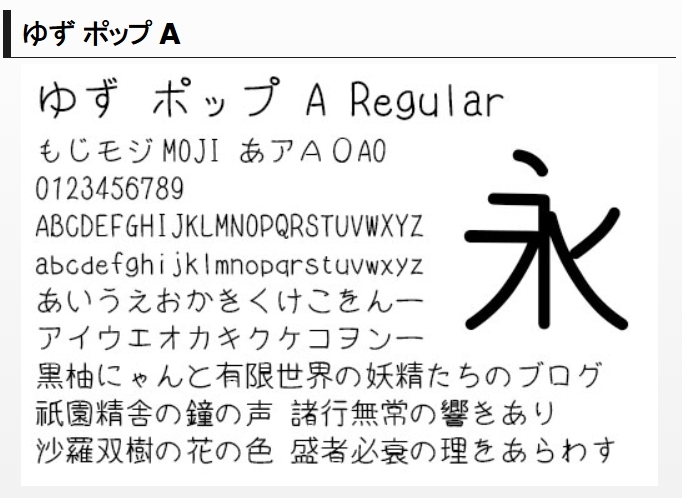
ハンまるゴシックは半角のように見える、細長のゴシック体フォントです。細めの見た目なのに丸っこく、かわいらしさとスタイリッシュさを兼ね備えているので、様々なシーンに使えるフォントとなっています。
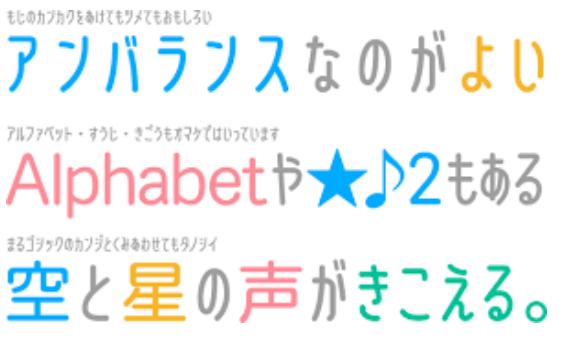
ちはや角は名前の通りカクカクとしたデザインのフォントです。カクカクはしていますが、独特のかわいらしさがあり、他では見ない珍しいデザインとなっています。
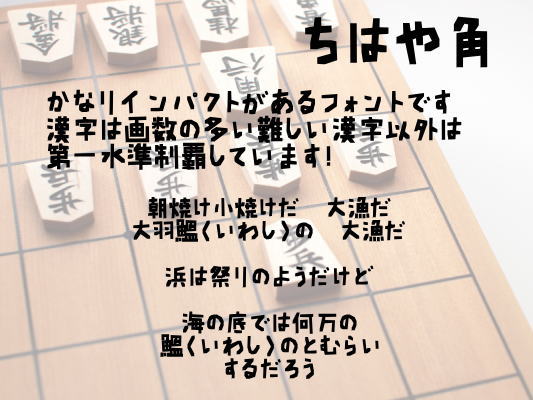
ribbonはリボンでできたような見た目のフォントです。可愛らしく、かつレトロな雰囲気もあり、特に女性の目を引くデザインとなっています。
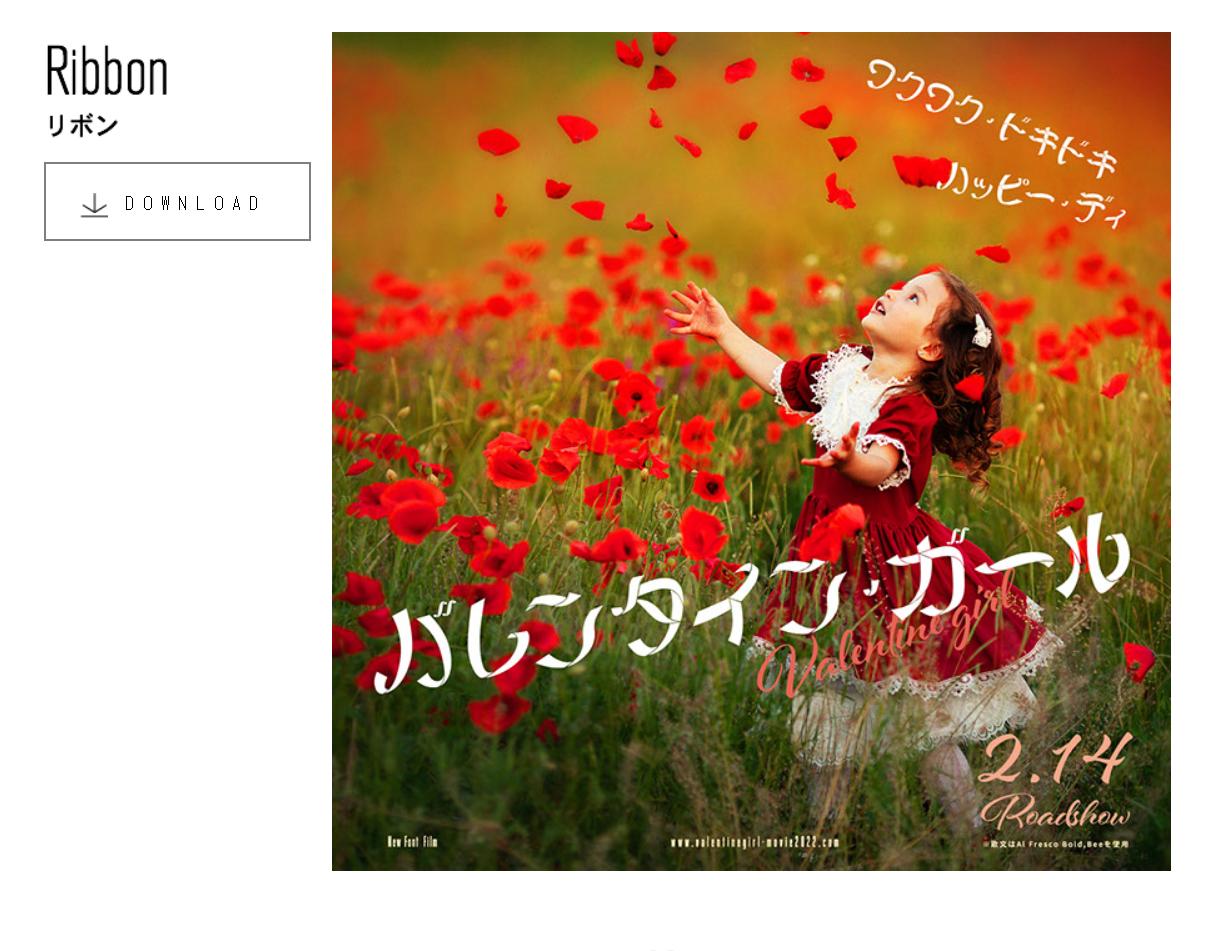
モギハ・ペン字は万年筆で書いたような雰囲気を楽しめるフォントです。かわいらしさの中に、凛とした美しさが感じられます。
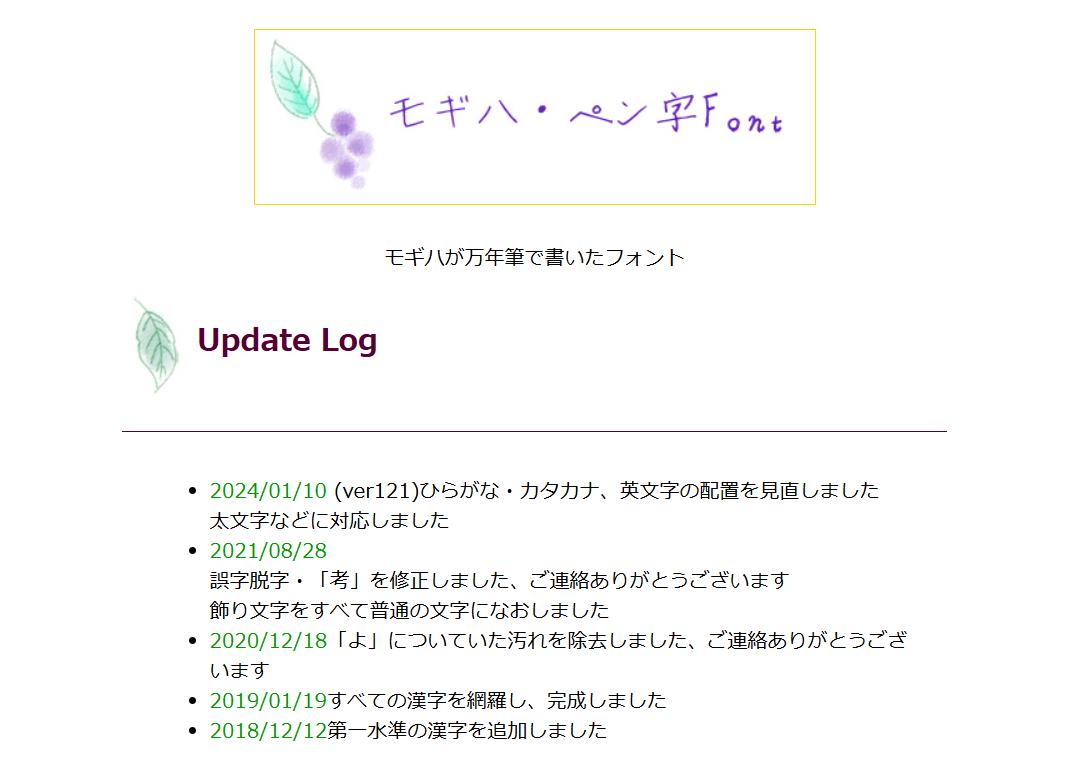
キリンフォントは名前の通り、キリンのように細長いフォントです。細長くカクカクとしていて、かつ太さもあるフォントなので、デザイン性が高く読みやすさもあります。
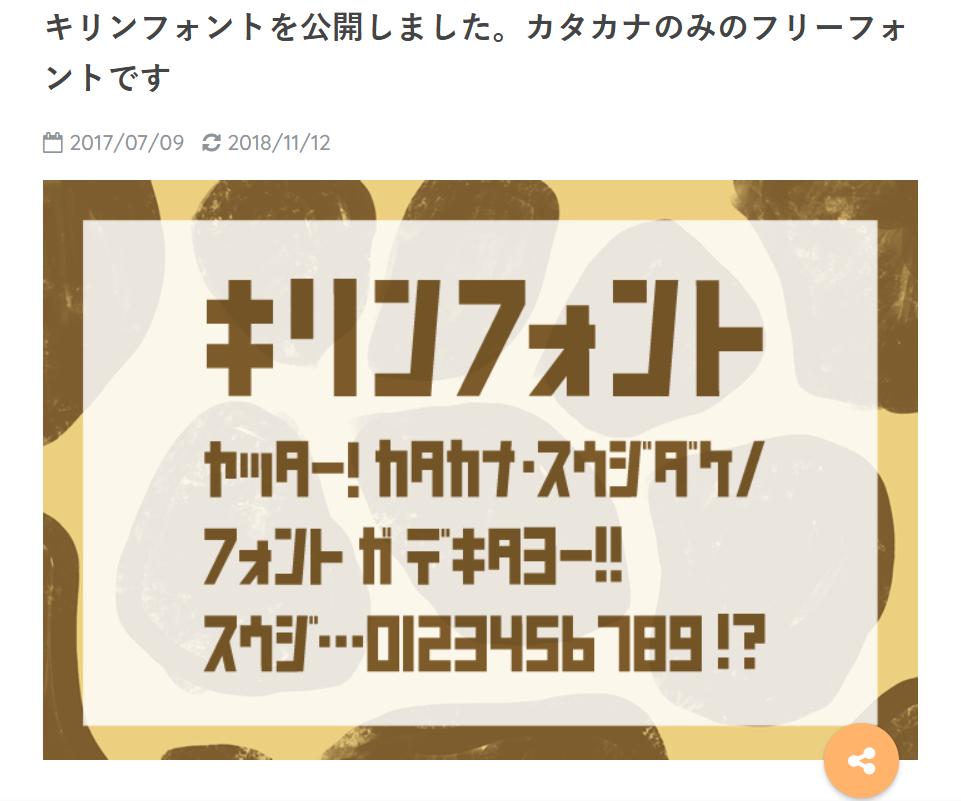
MPRばるーんは全ての文字のグリフに風船のシルエットが入っているフォントです。バルーンのシルエットが表示されるので、タイトルや見出しに使うと非常に目を引きます。
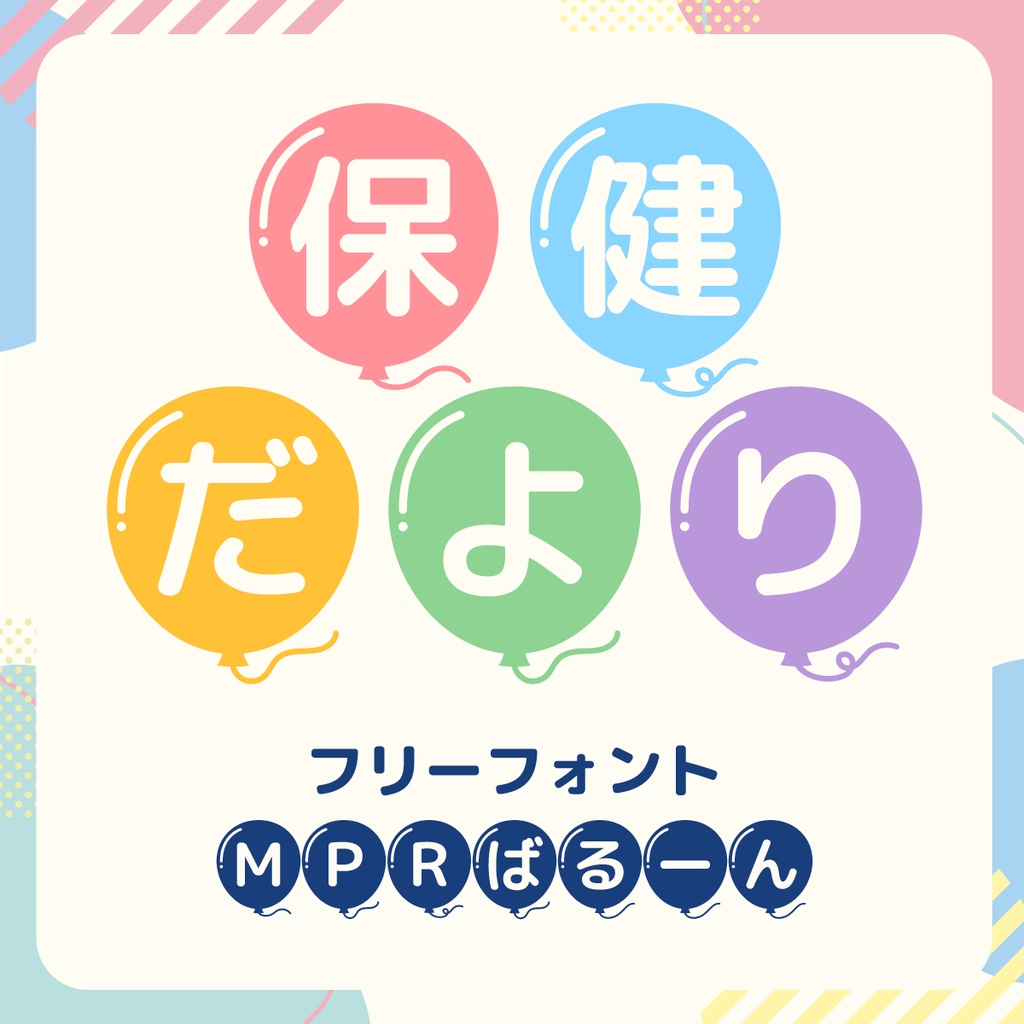
塩化速記は手書きで速記したような見た目のフォントです。柔らかな雰囲気と、リアルな手書き感が印象的なデザインとなっています。
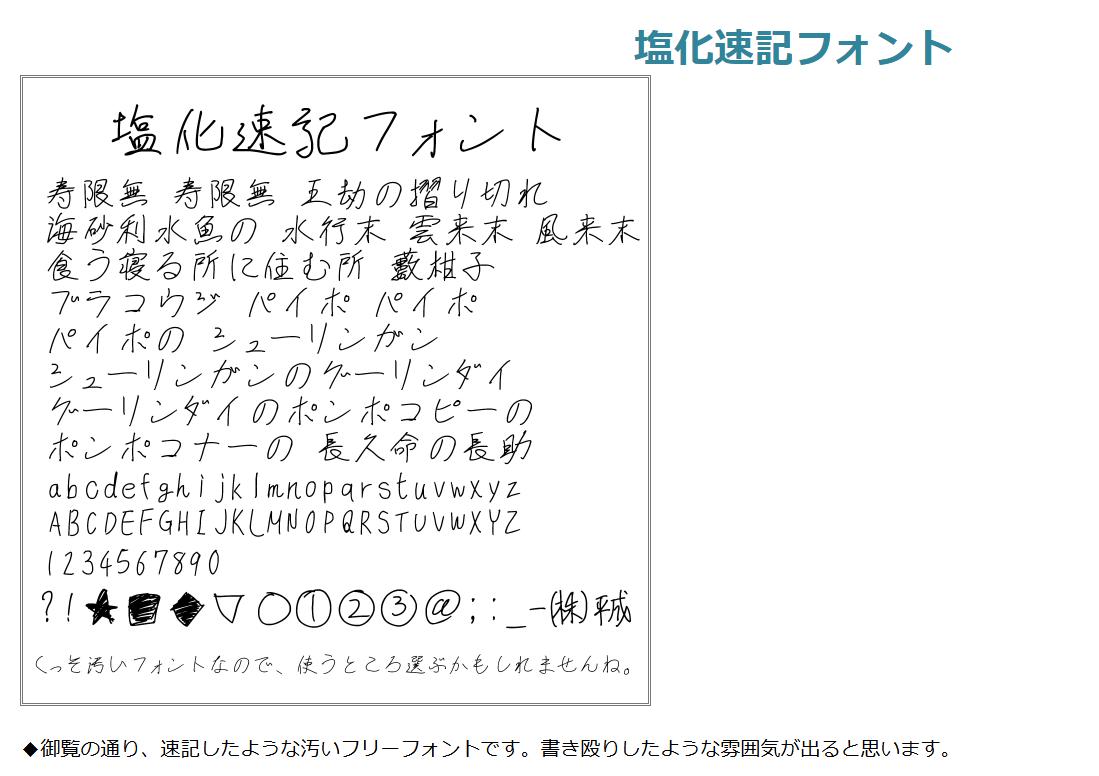
ちひろもじ
ちひろもじは、昔ながらの丸文字やギャル文字のような雰囲気のあるかわいらしいフォントです。手書きの温かみがありながら可視性も高いため、使い勝手が良いです。
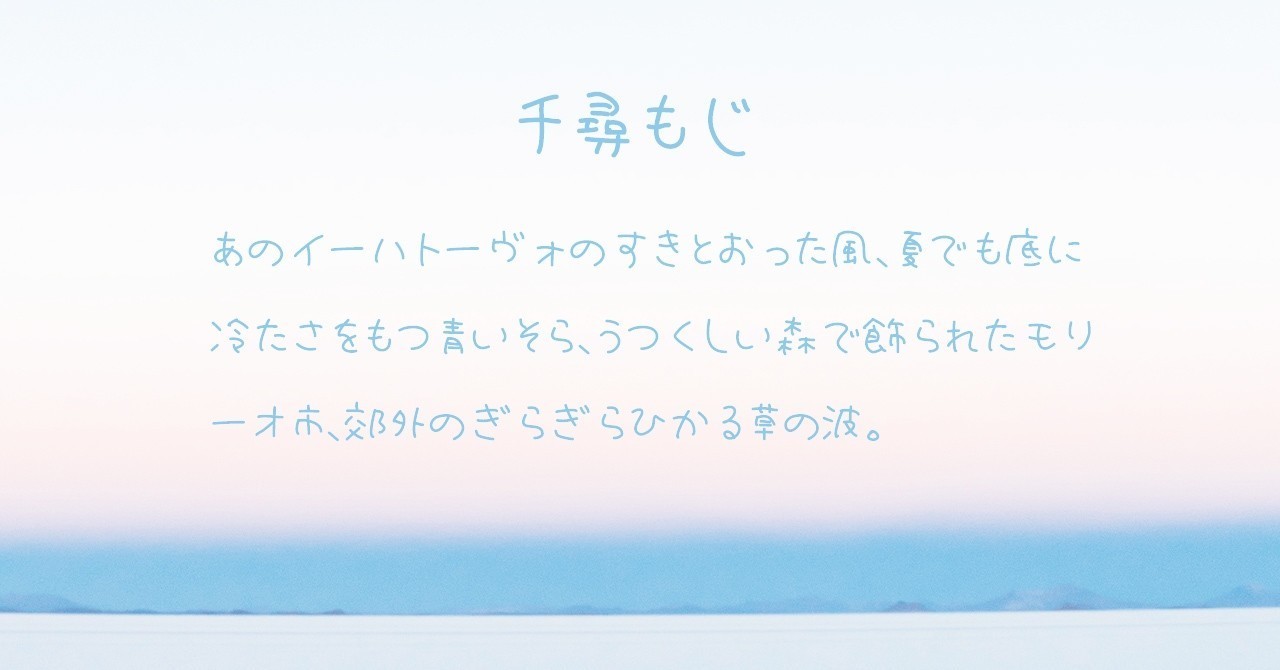
にくまるフォントは太字のぷっくりとしたフォントです。不規則な形が面白く、使い方によっては非常に目を引く文章やデザインにすることができるでしょう。
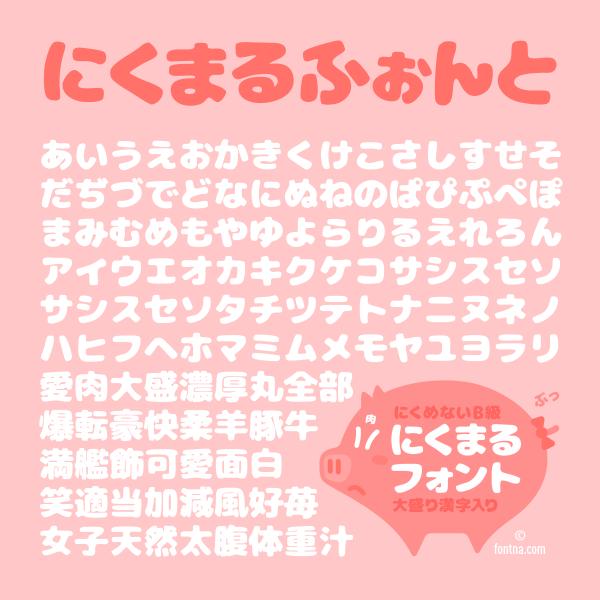
かわいいフォントには手書き風の温かみがあったり、丸みのあるフォントが多いです。これらの特徴は、視覚的に柔らかく、親しみやすい印象を与えるのに効果的です。特に子供や女性に向けた製品のパッケージに活用すると、好印象を持ってもらいやすいでしょう。